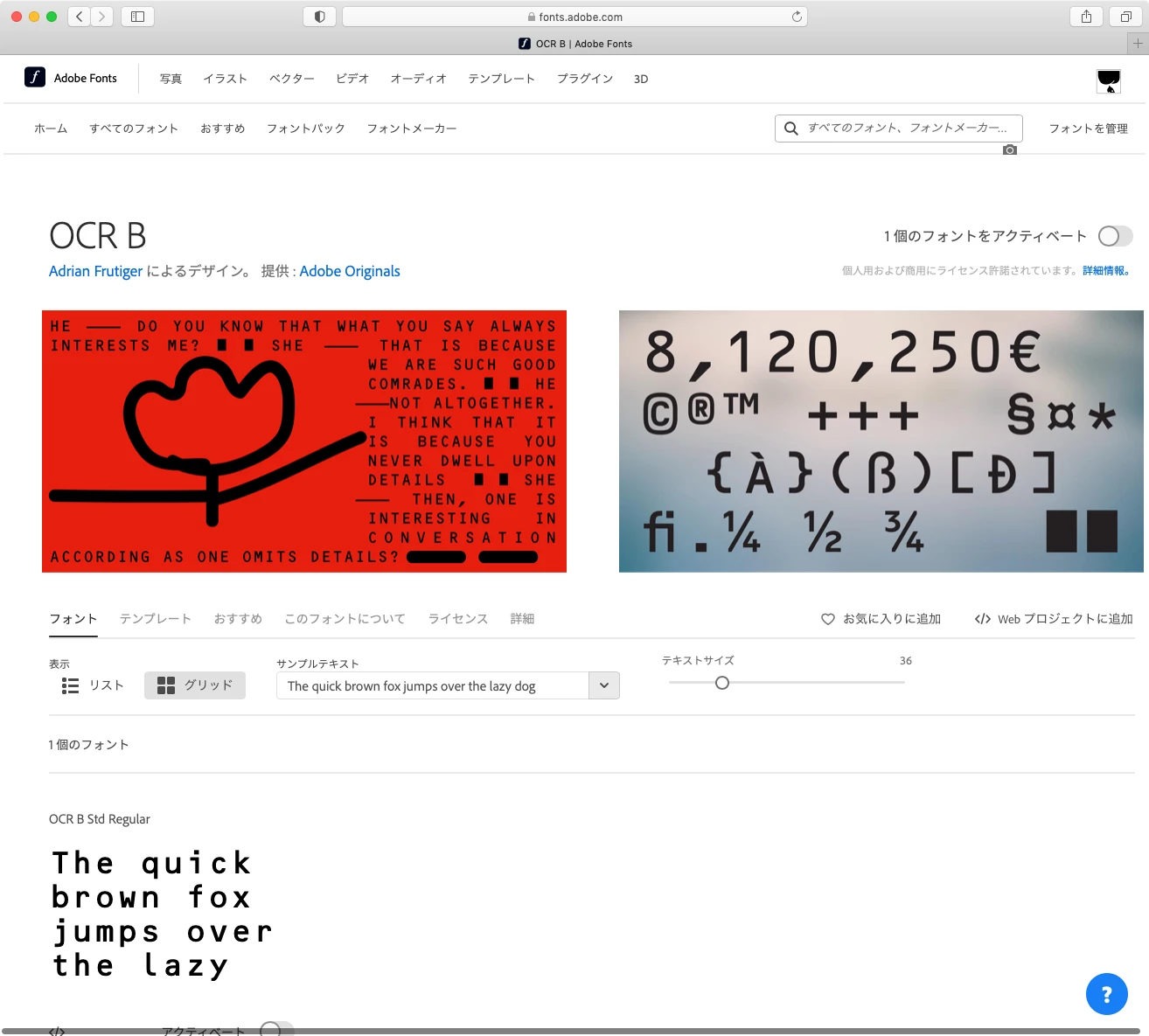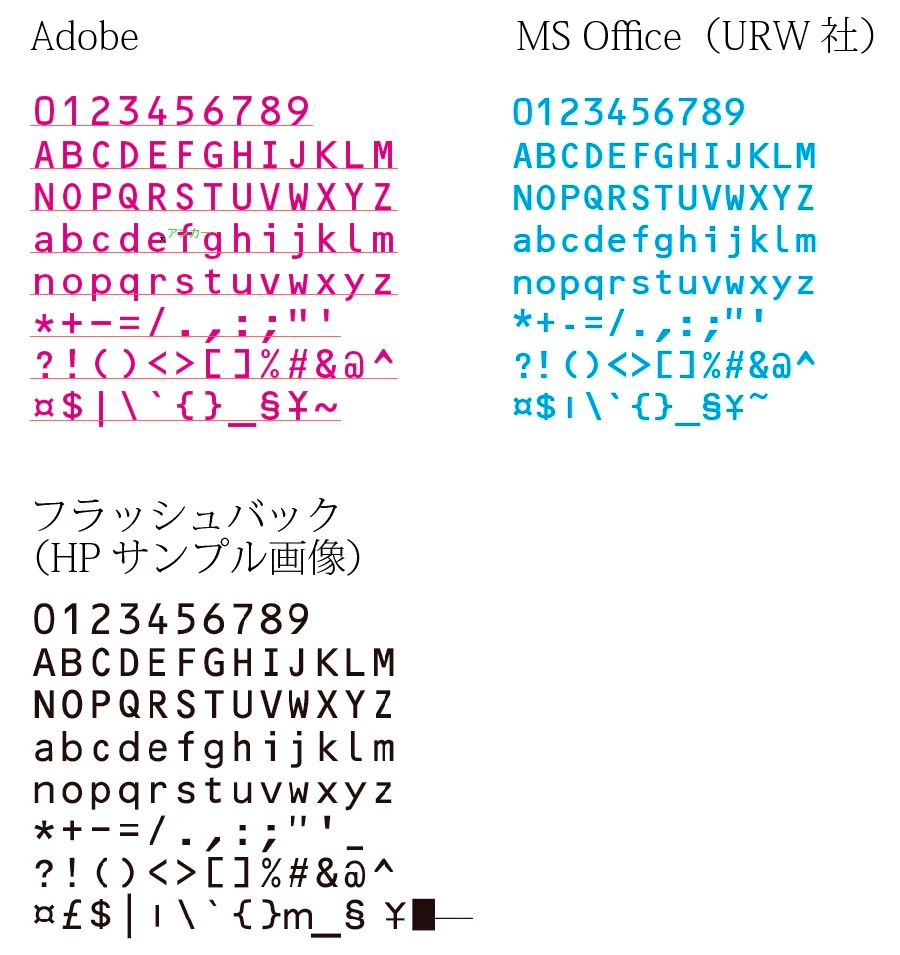
JIS規格 OCR-B  フォントの数字を使いたいのですが、どうすれば良いですか。
規格自体はuser2840291さん指摘の通りISOとJISは互換性がありますのでAdobeFonts提供のものが利用可能ですね。
わたしも郵便振込用紙やバーコード添付の数字などで使っています。
OCRフォント自体ISO規格なので、ISO基準に日本向けに改良されているのがJIS規格だとすれば、数字だけならなんでもいいんじゃないでしょうか。
JIS規格にこだわるとしたらOCR-Kなどのカタカナなどのバージョンでしょうか。
私のところではAdobeのOCR-Bで問題になったことはないです。
ただ、MS Office付属のOCR-BはAdobeのものより同じポイントでも若干小さく、また字間が詰まり気味な感じで何か不安すね。
もしかしたら機械で読み取れないなどがあってMS Office付属のOCR-Bは使うなということでしょうかね。
通常でいえばajabonさんの仰るようにAdobe Fontsで入れたり、WindowsであればOS標準のものでも済むと思います。
おそらく、OCR-Bの利用を誰かに指示されていると思うので、その方にどれを使うべきか、どれでもいいのかを確認されたほうがいいのではないかと思います。
(JIS規格の文字サイズやピッチに完全適合しなければならないかどうか、という点があると思います)
Adobe Fontsにありますよ
すみません、JIS X 9001準拠のほうですね。